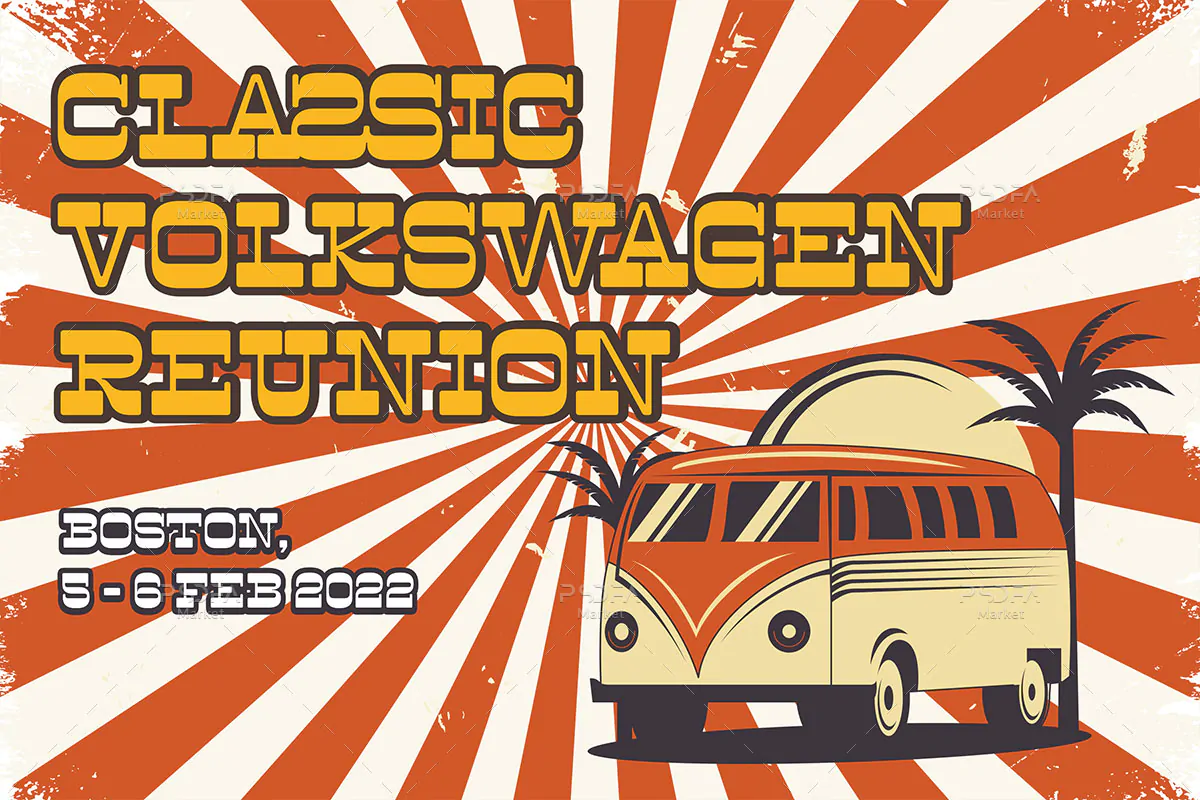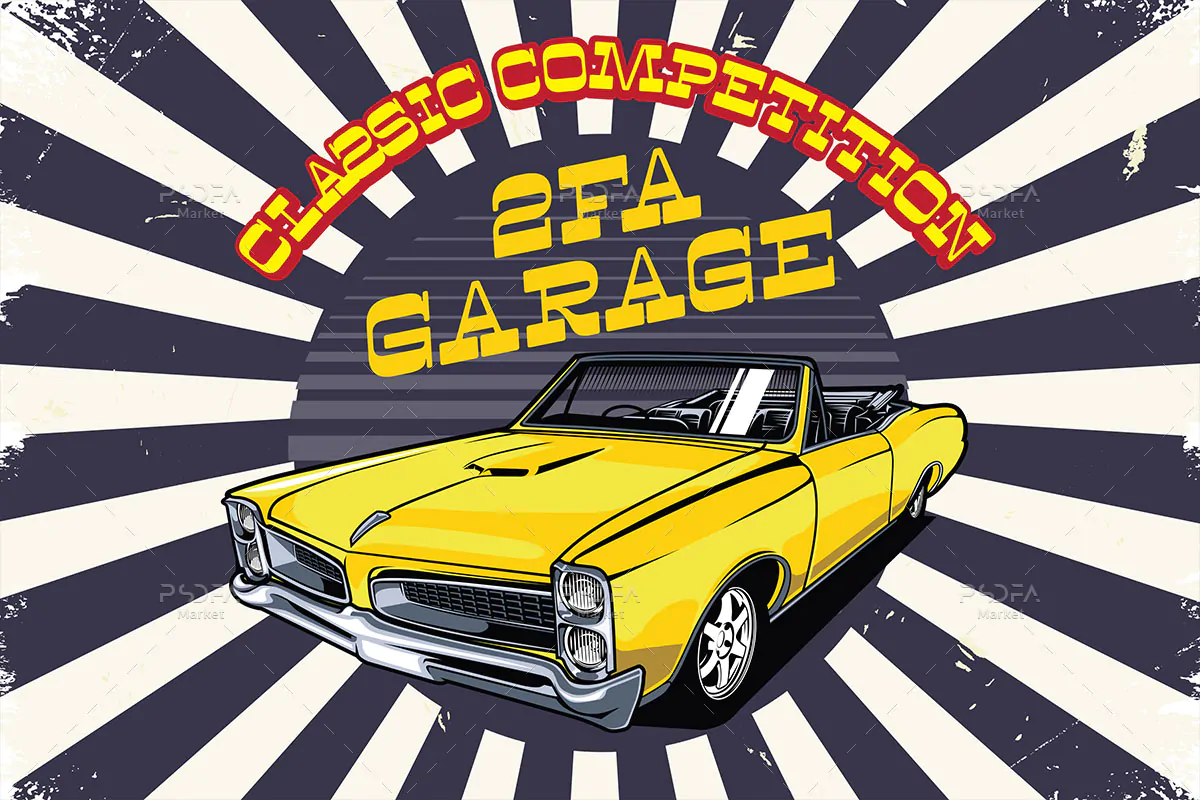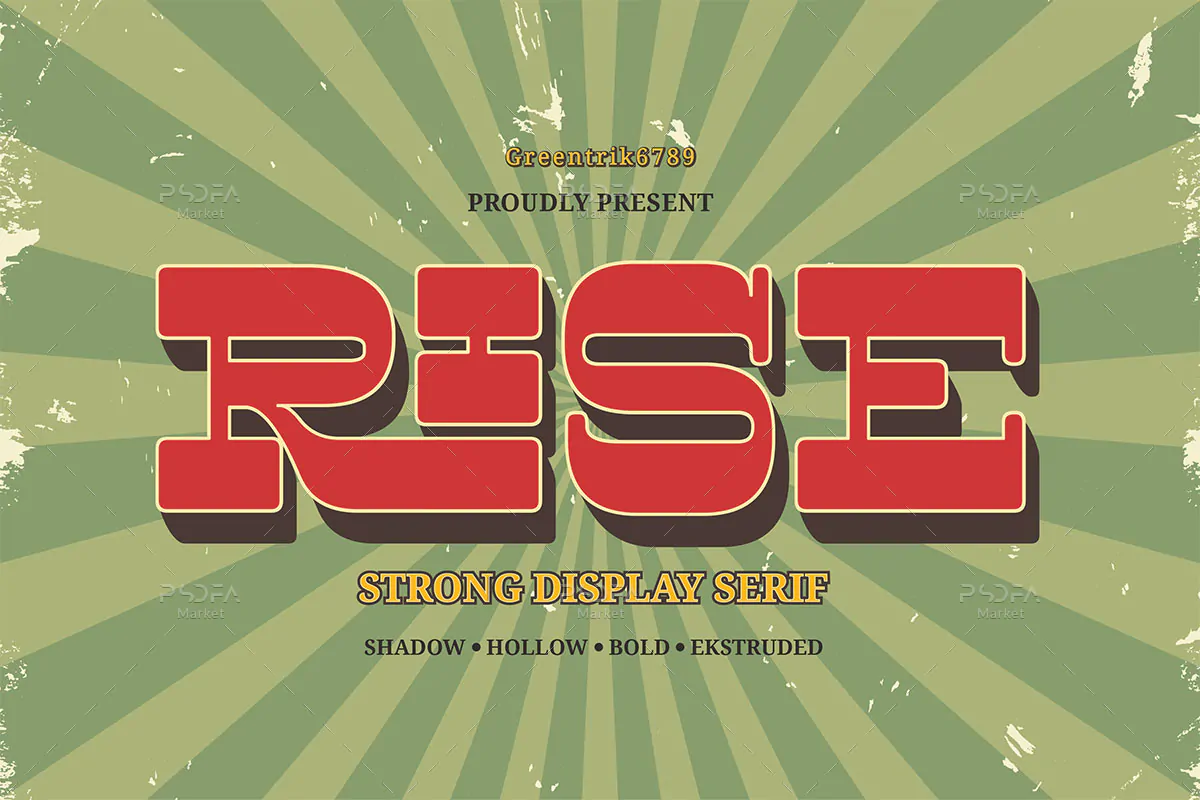
فونت کلاسیک و رترو انگلیسی Rise
فونت کلاسیک و رترو
فونت کلاسیک و رترو انگلیسی Rise یک قلم نمایشی فوق العاده زیبا است که مناسب جهت استفاده در طرحهای گرافیکی مختلف میباشد. فونت Rise در 5 سبک و وزن Regular, Bold, Outline, Shadow, Extruded طراحی شده است که میتوانید از آن در طراحی انواع پوستر، تیشرت، بسته بندی محصولات، ظروف یکبار مصرف، لوازم التحریر و … استفاده کنید.
- وزن: Regular, Bold, Outline, Shadow, Extruded